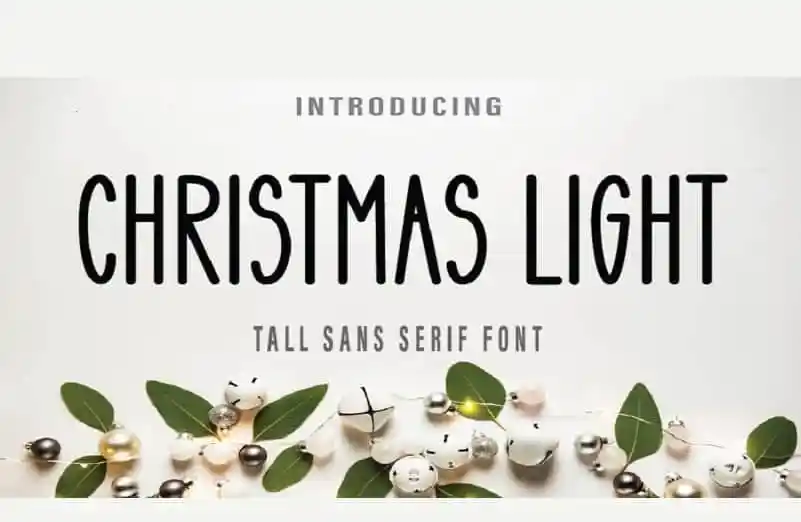
Christmas Light Display Font – Download Grátis
Christmas Light Display Font é uma elegante fonte sans-serif que traz ao seu design uma aparência simplesmente encantadora e divertida. Suas linhas levemente curvadas se assemelham a luzes de Natal entrelaçadas, criando um visual vibrante e brilhante. Este recurso gráfico é perfeito para o natal ou até mesmo para qualquer outro evento que exige uma atmosfera festiva. Seu estilo natural e único tornam-se tão atraentes quanto a luz de um grande parque de diversões durante as férias de final do ano, criando um design visual impactante. Para designers que buscam algo além da monotonia tradicional das fontes serifa, este é o texto ideal para adicionar uma pitada de encanto e vibrância à sua próxima criação gráfica.